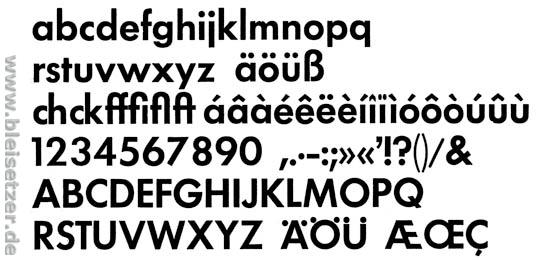
Typo aus der Serie "Lost" (mit Bild)
Habe neulich die schöne nüchterne Typografie in den Credits von Lost gesehen.
Ich konnte leider nur einige Fotos direkt vom Fernseher schießen. Dem entsprechend ist die Qualität nicht besonders.
Aber vielleicht hat ja jemand eine Vermutung, welche Schrift das ist.
Ja, ich schließe mich an.
Futura dreiviertelfett von Paul Renner.
Bauersche Gießerei, 1930
An Futura habe ich zunächst gedacht, aber dann sind mir die kleinen Buchstaben aufgefallen.
Besonders das kleine "a" oder das "d" passen nicht ganz dazu.